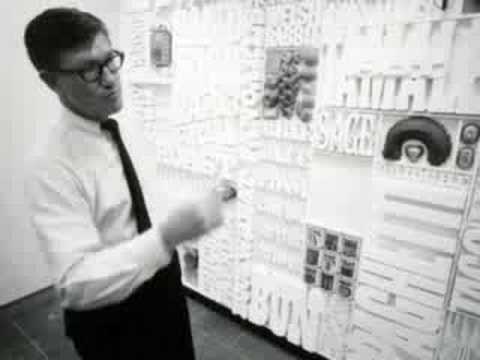
Typograph Lou Dorfsman gestorben
Die form berichtet heute über den Tod von Lou Dorfsman, der zuletzt als Art Director für die CBS tätig war:
Der ehemalige Art Director der CBS, Lou Dorfsman, ist am 22. Oktober im Alter von 90 Jahren verstorben. Seine Arbeit im Bereich Werbung und Corporate Identity für die Columbia Broadcasting Company prägte das Verständnis von Unternehmenskommunikation und Branding bereits in den 50er Jahren nachhaltig. Mit seiner schlichten Typografie und seinen pointierten Illustrationen entwickelte er einen eigenen Stil, der konzeptionelle Klarheit und eine provokative visuelle Präsentation gekonnt kombiniert. Bereits 1978 wurde er in die Art Directors’ Hall of Fame aufgenommen und erhielt die American Institute of Graphic Arts Medal für sein Lebenswerk.
Lou Dorfsman erhielt 1995 die TDC-Medal des Type Directors Club und wurde generell durch seine typografische Gestaltung weltweit bekannt. Hier eine Fotografie von ihm in jungen Jahren, vor dem damaligen CBS Logo:
Hier einige seiner Arbeiten:
Bei YouTube gibt es auch ein 4,5 minütiges Video, das Lou Dorfsman zeigt, der über die bekannte CBS Wall und ihrer Entstehung erzählt:
Weitere Eindrücke seiner Arbeit kann man sich auch bei Speak Up machen, dort wurden jede Menge Fotografien zusammengetragen.